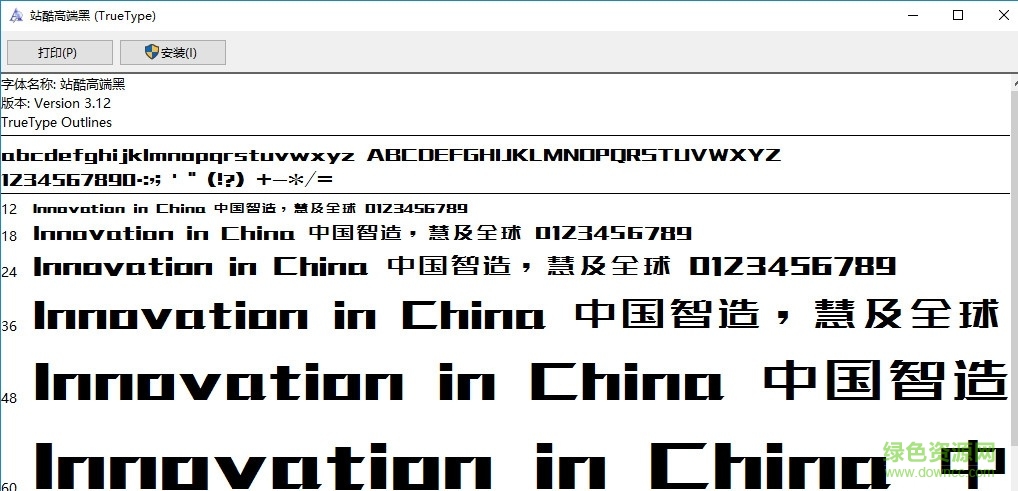
huxiaobo gdh字體又叫站酷高端黑字體,是由胡曉波所設(shè)計的一款免費字體,筆畫粗獷,線條簡潔,個性鮮明,設(shè)計感強(qiáng)烈,適合用于男性廣告、游戲、體育宣傳等領(lǐng)域,需要的朋友歡迎下載使用!
字形筆畫粗獷有力、用寬扁型的字面構(gòu)建出厚重的字體形態(tài),筆畫細(xì)節(jié)上的修飾既增強(qiáng)了字體的設(shè)計感,又讓字體多了一些小小的精致感。
該字體與方正尚酷黑、方正譚黑、造字工房力黑及蒙納超剛黑相似,由數(shù)十位設(shè)計師共同創(chuàng)作,透過字體傳達(dá)出銳氣、進(jìn)取與力量,具有良好的觀賞性與設(shè)計感,可以廣泛應(yīng)用于廣告設(shè)計、宣傳海報、ppt、影視制作以及任何使用文字的領(lǐng)域!